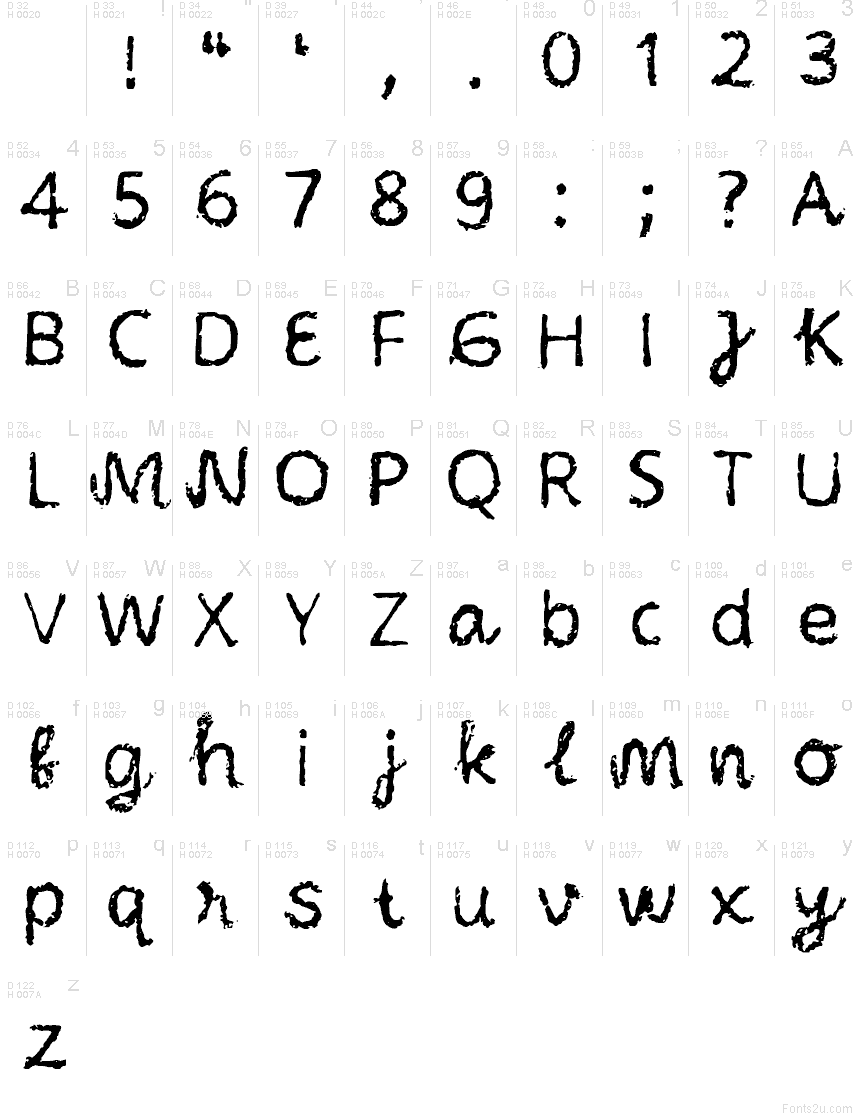
Marisas Pencil Handwrit Regular
Marisas Pencil Handwriting es una tipografía manuscrita gratuita con ese toque de apunte escolar algo desordenado. Las letras lucen irregulares y como frotadas, con trazos gruesos, bordes temblorosos y pequeñas interrupciones que hacen que la escritura se sienta rápida, humana y ligeramente emborronada, en lugar de algo perfectamente practicado.
Es ideal para pósteres escolares, títulos de álbumes de recortes, portadas de libros infantiles, encabezados de fanzines y packaging artesanal donde un garabato informal queda mucho mejor que una rotulación pulida. Al ser una fuente gratuita, también funciona muy bien en gráficos de frases cortas o tarjetas de título, especialmente cuando buscas que las palabras parezcan dibujadas a mano y con un toque rebelde.